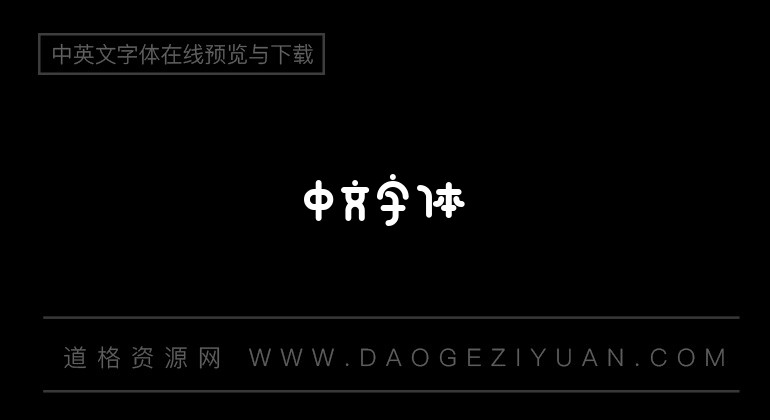
锐字工房卡布奇诺粗简
锐字工房卡布奇诺粗简字体是一款拥有粗简风格的英文字体,它具有粗犷的线条,显示出坚定的意志和果断的行动。这种字体适用于拥有现代感的设计,如品牌标识,海报,海报等。锐字工房卡布奇诺粗简字体具有清晰的轮廓,大胆的线条,以及出色的可读性,可以提升您的设计的吸引力。
锐字工房卡布奇诺粗简是一款非常不错的手写艺术字体,具有很好的视觉感,适合于文化类的宣传设计、商业类品牌的广告和产品包装设计以及个性化文字排版等较多场景。